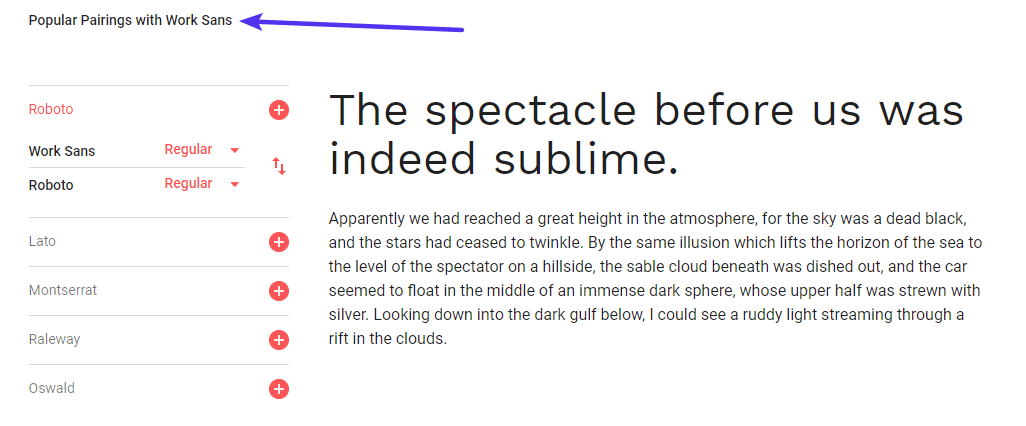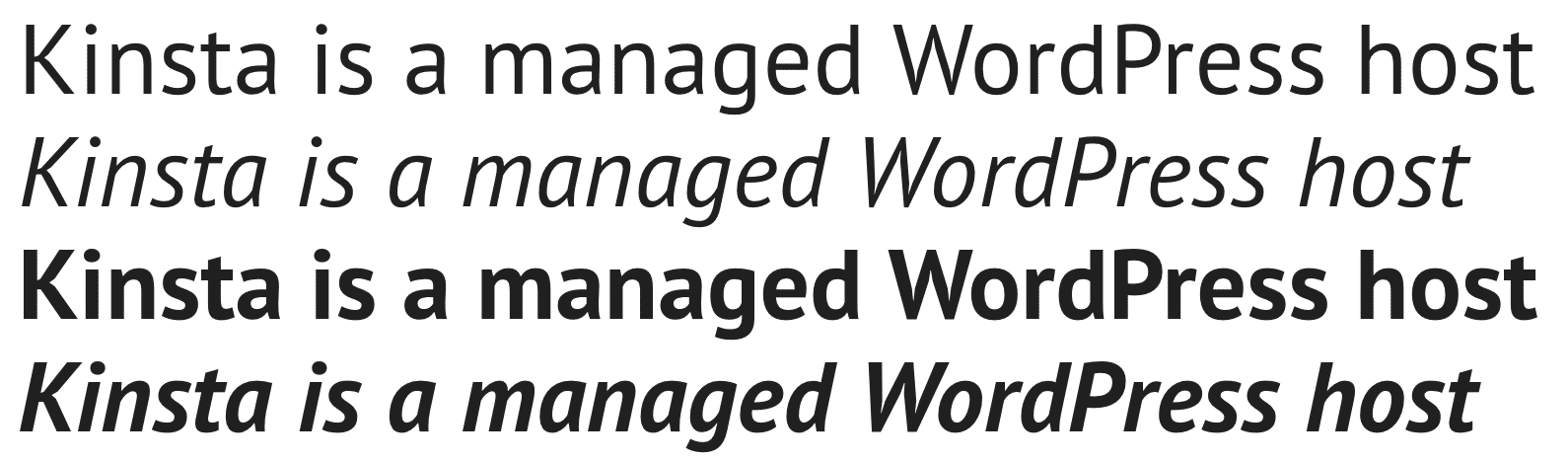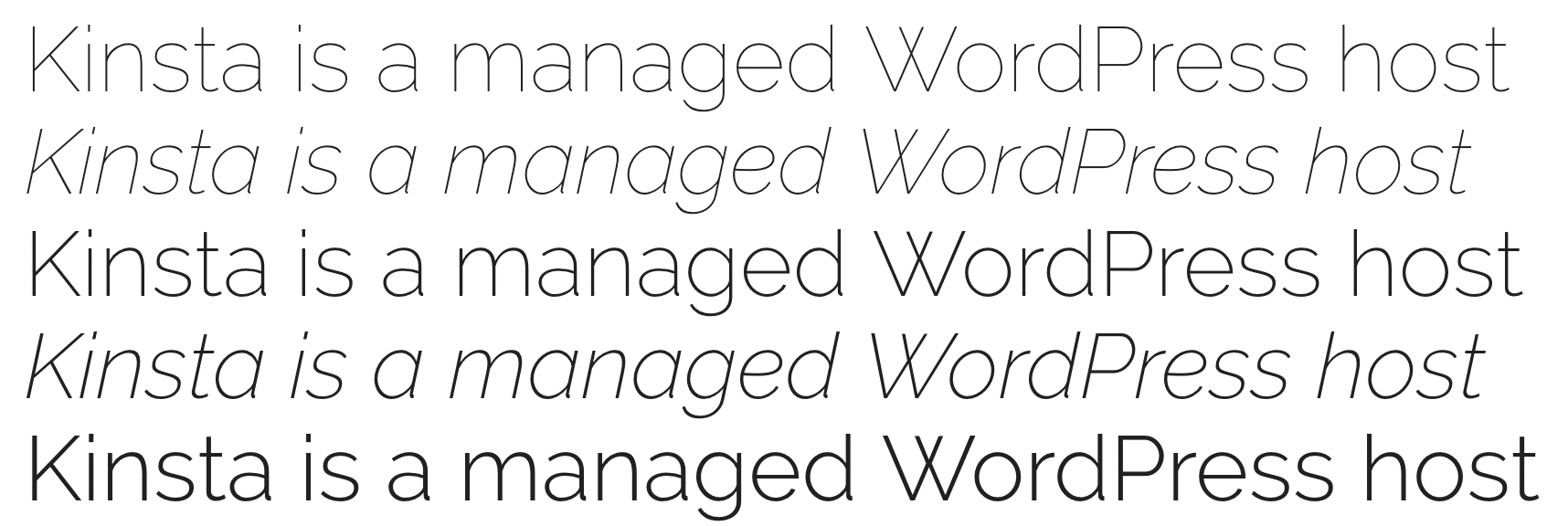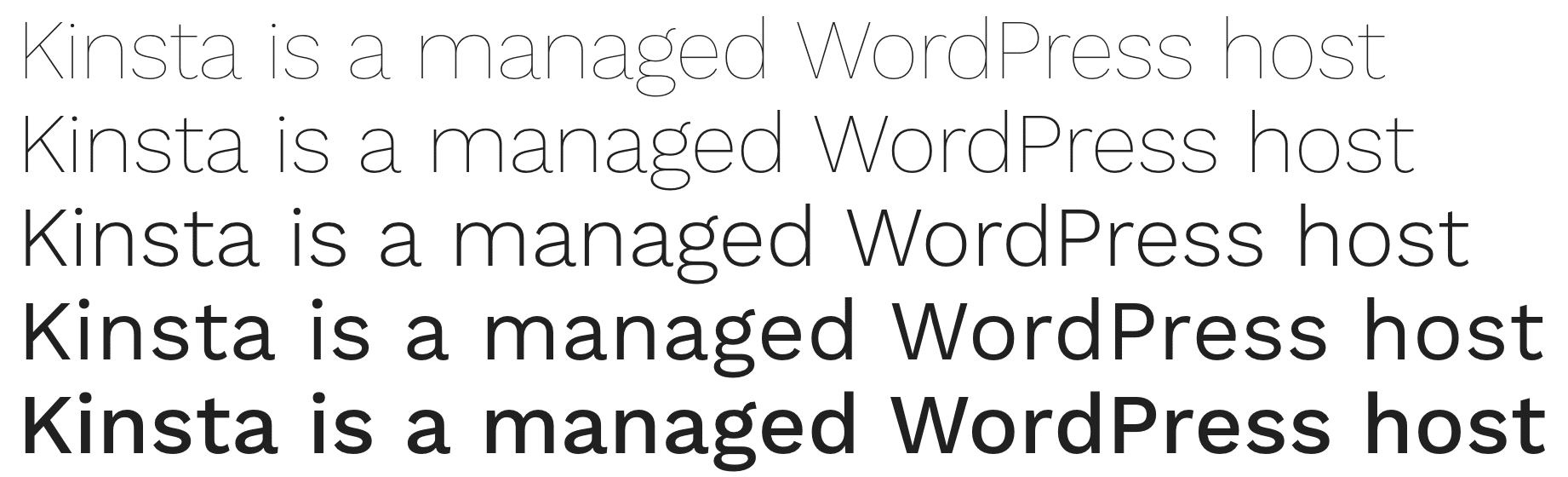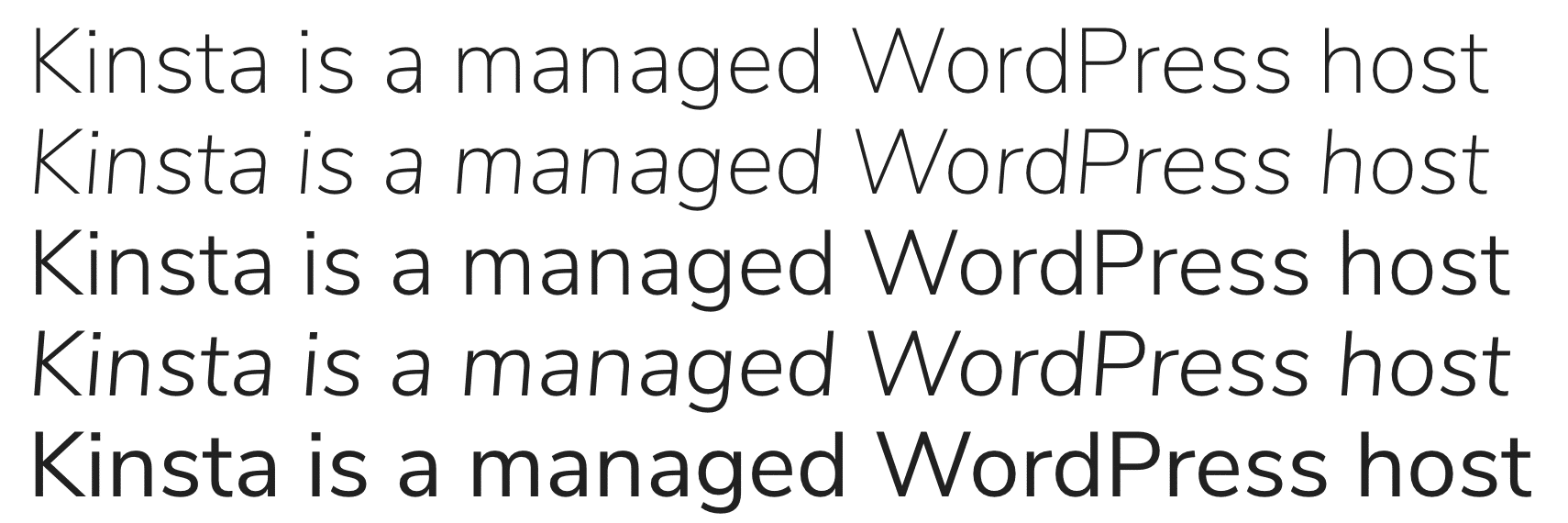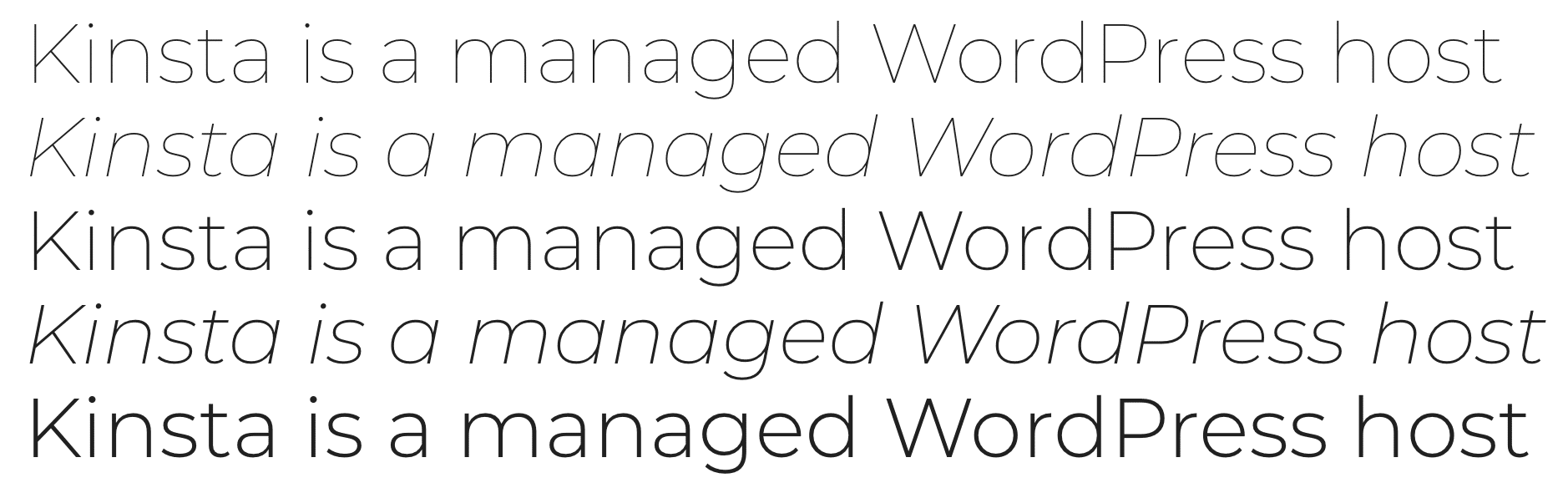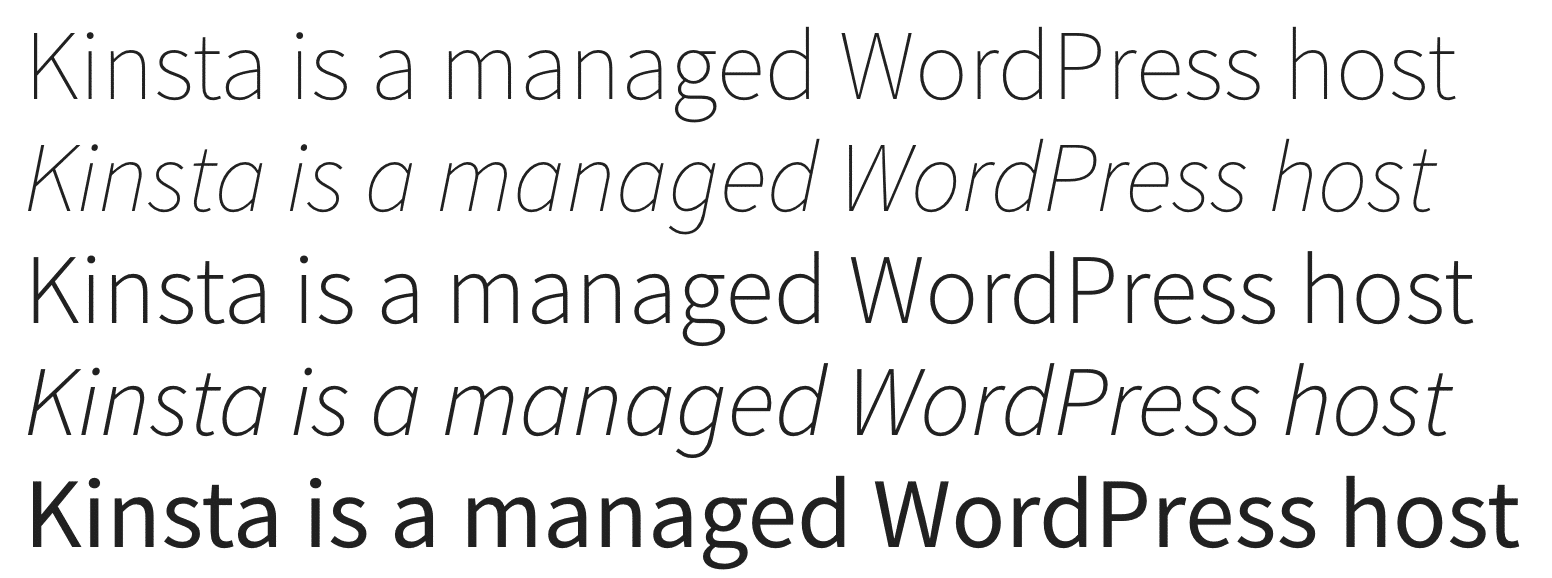
Existen 1052 familias diferentes de fuentes en Google Font disponibles de forma gratuita (en el momento de escribir este artículo). ¡Eso significa que hay un montón de opciones! Así que no es de extrañar que necesites ayuda para encontrar esa aguja en un pajar con una lista con las mejores fuentes en Google Fonts.
Lo tenemos para ti, y luego también compartiremos algunas de las mejores prácticas para usar Google Fonts en WordPress.
La elección de una fuente es algo más que una opción estética: puede tener un efecto sustancial en las tasas de rebote y las tasas de conversión de tu sitio, especialmente si eliges una fuente difícil de leer. Por lo tanto, vale la pena tomarse un poco de tiempo para elegir la familia de Google Fonts perfecta para tu sitio web, en lugar de utilizar la primera fuente que encuentres.
¿Por qué utilizar Google Fonts?
Hay miles de repositorios de fuentes en Internet, así que ¿qué hace exactamente que Google Fonts sea tan especial?
En primer lugar, es gratuito. Además, las fuentes de Google son mantenidas y entregadas por Google, lo que significa que están garantizadas. Por supuesto, existen un montón de sitios web dudosos en los que puedes descargar fuentes gratuitas, pero ¿quién sabe qué más puedes encontrar con esos archivos?
La calidad de las fuentes de estos sitios web también puede ser a veces cuestionable.
Google ha reunido una selección de más de mil fuentes de alta calidad. Cuando no eres un diseñador gráfico con un ojo perfecto para la tipografía, es una opción más segura.
Aunque las fuentes de Google tienden a ser simples y quizás no tan llamativas como algunas fuentes de pago, sin duda son mejores que las fuentes seguras para la web que vienen preinstaladas con los principales sistemas operativos, las mismas fuentes que todo el mundo ha visto miles de veces.
Qué buscar en una fuente de Google
Si hay algo que debes aprender al diseñar un sitio web, es cómo elegir una fuente de Google Font adecuada para tu proyecto. Una buena tipografía hará bueno o romperá tu sitio.
Puede parecer un detalle sin importancia, pero puede ser la diferencia entre que alguien abandone tu sitio antes de tiempo o se quede para convertirse en un lector o cliente fiel.
La elección de la fuente correcta es algo que los diseñadores gráficos pasan años dominando, pero si se tienen en cuenta algunos principios, se puede elegir una fuente hermosa para tu sitio web.
- Se ajusta a tu marca: Este puede ser el aspecto más crítico. Los mejores sitios web tienen un tipo de letra que muestra tu personalidad al mismo tiempo que es legible y encaja con el diseño actual. Por ejemplo, Apple y Iron Maiden utilizan fuentes muy diferentes, pero ambas se ajustan a su marca.
- Legibilidad: El segundo principio más importante es la legibilidad. Un tipo de letra de fantasía o grunge puede encajar con tu marca, pero si tus visitantes no pueden leerlo, se irán rápidamente. Por lo tanto, tus fuentes deben ser profesionales y legibles.
- Clasificación de los tipos de letra: Aunque hay cientos de maneras de clasificar un tipo de letra, estos son los cinco tipos principales: serif, sans-serif, script, monospace y decorativo. Las fuentes con guión o serif transmiten elegancia, mientras que las fuentes monoespaciadas son populares en los sitios tecnológicos. Conocer estas clasificaciones te darán un mejor punto de partida en tu búsqueda.
- Fuente de pantalla o cuerpo: Las fuentes de visualización son para tamaños grandes, cabeceras o proyectos de impresión. Pueden permitirse ser menos legibles en aras de un diseño único. La directiva principal de las fuentes corporales es la legibilidad, ya que constituirán la mayor parte de tu sitio.
- Estado de ánimo e intención: Al igual que cualquier obra artística, los artistas diseñan fuentes para estados de ánimo y entornos específicos. La mayoría de las fuentes vienen con notas sobre cómo fueron diseñadas y cómo se pueden utilizar. Utilízalas para decidir si la fuente se adapta a tu proyecto.